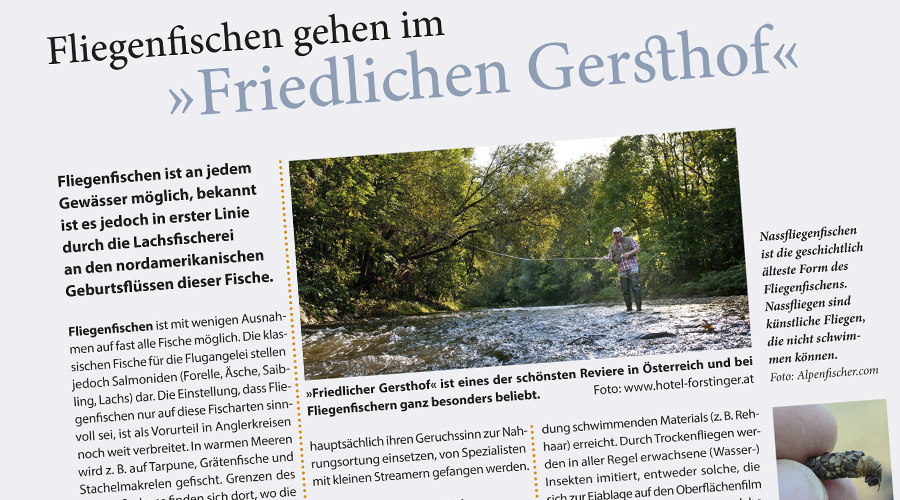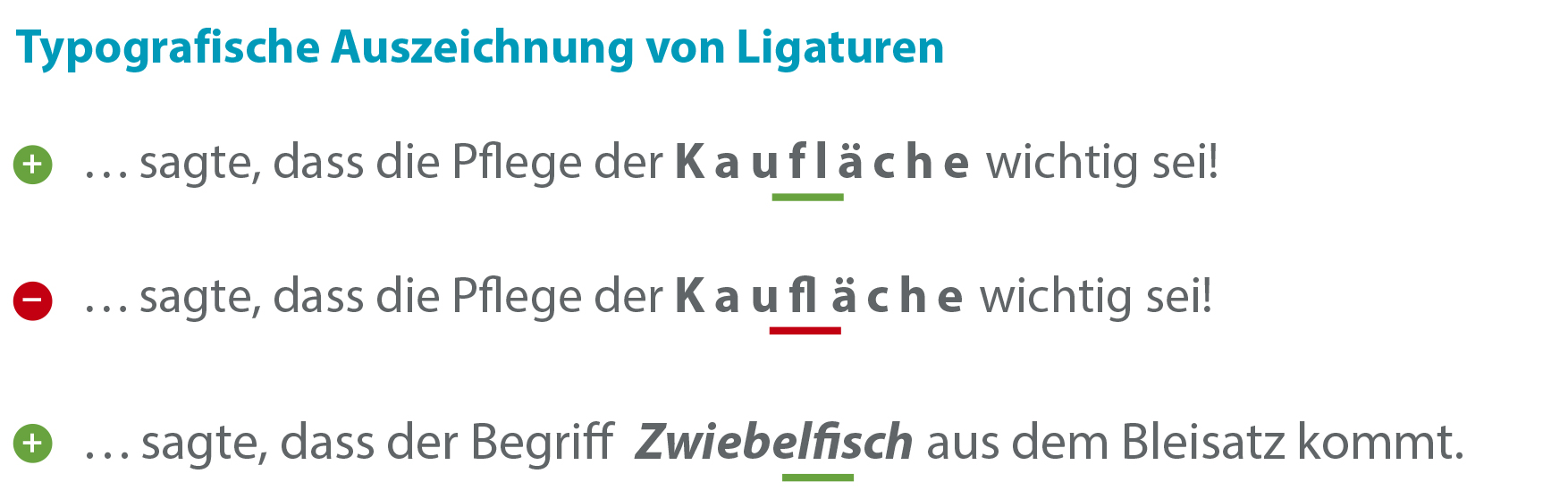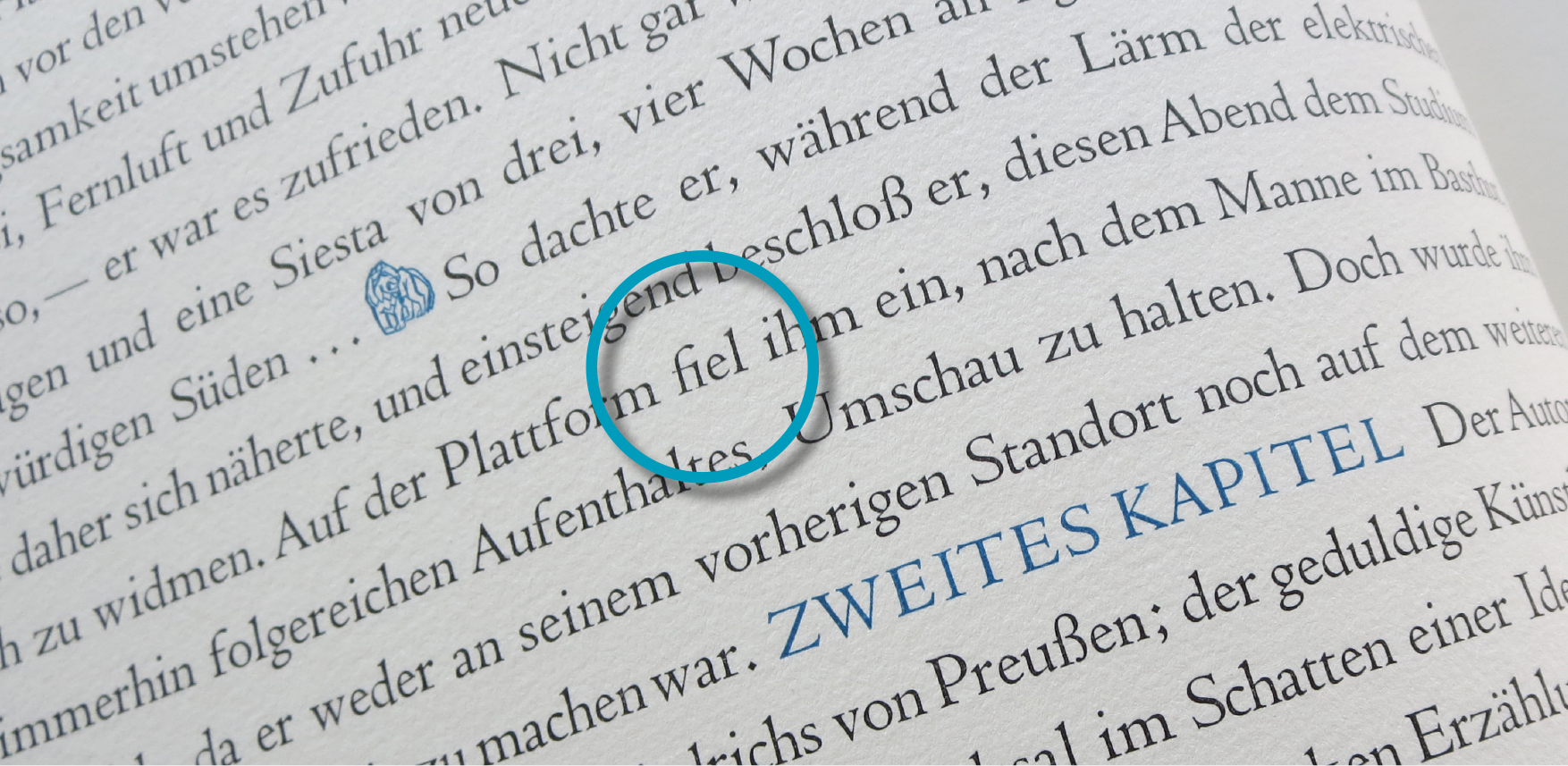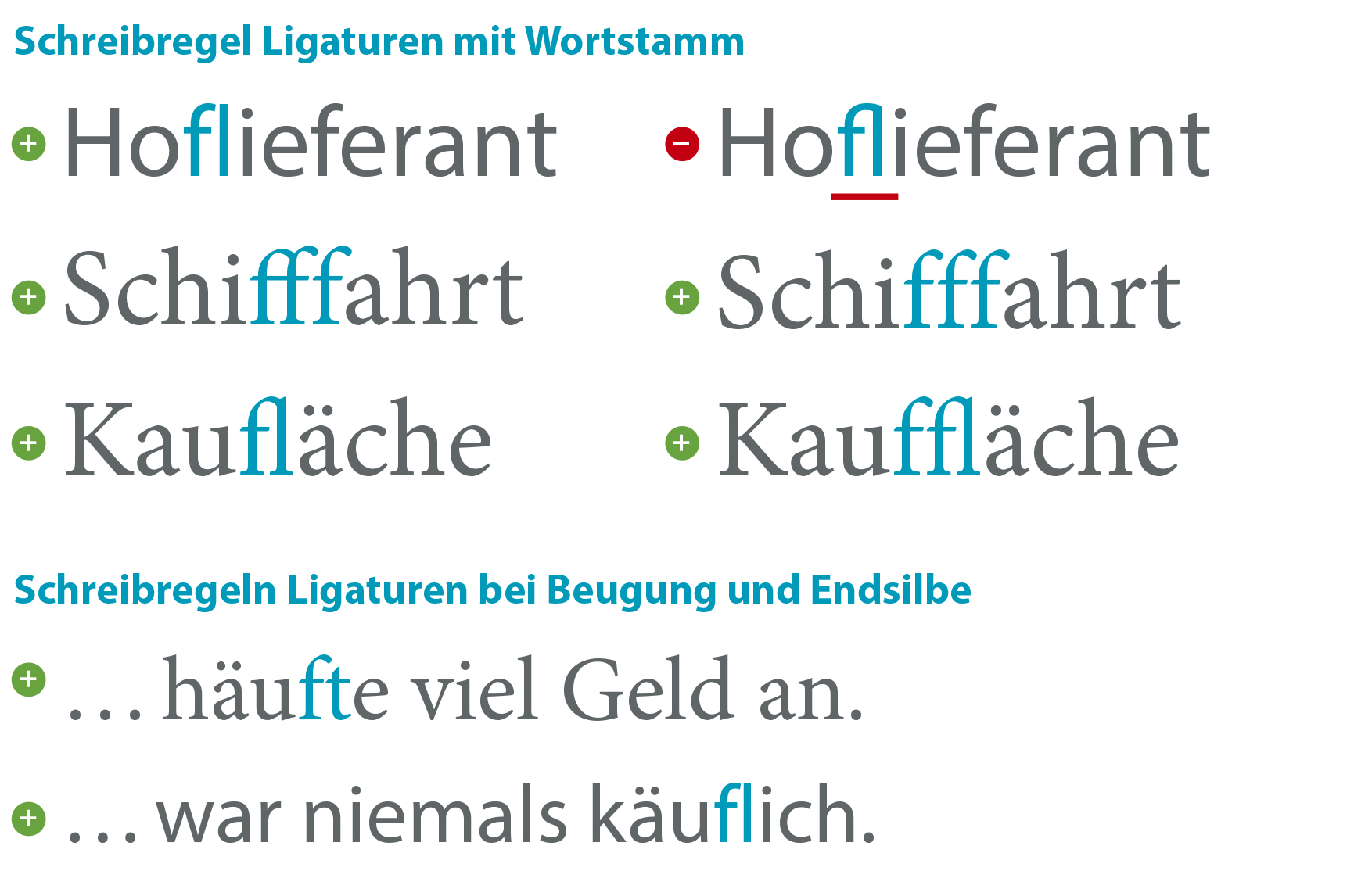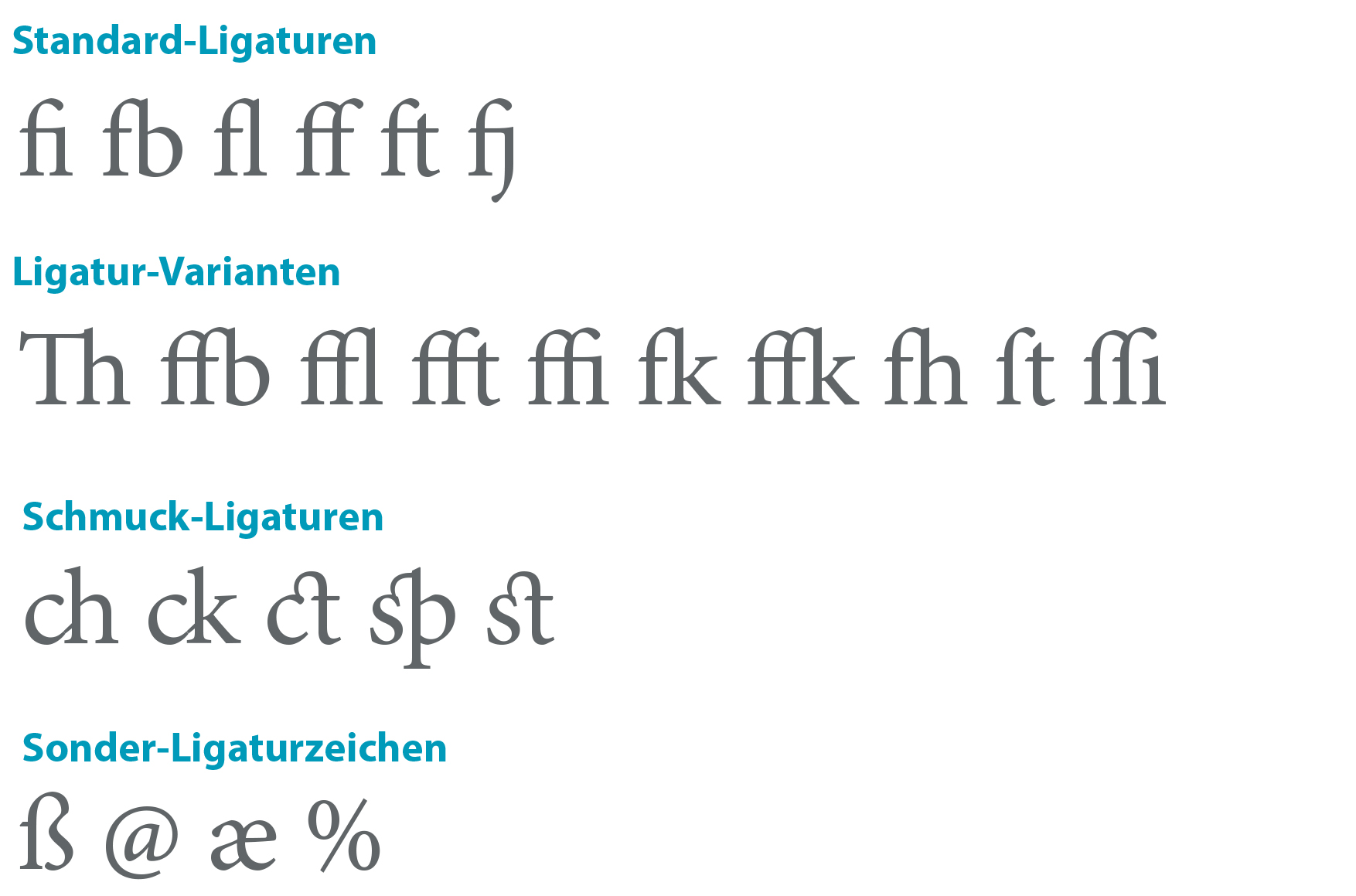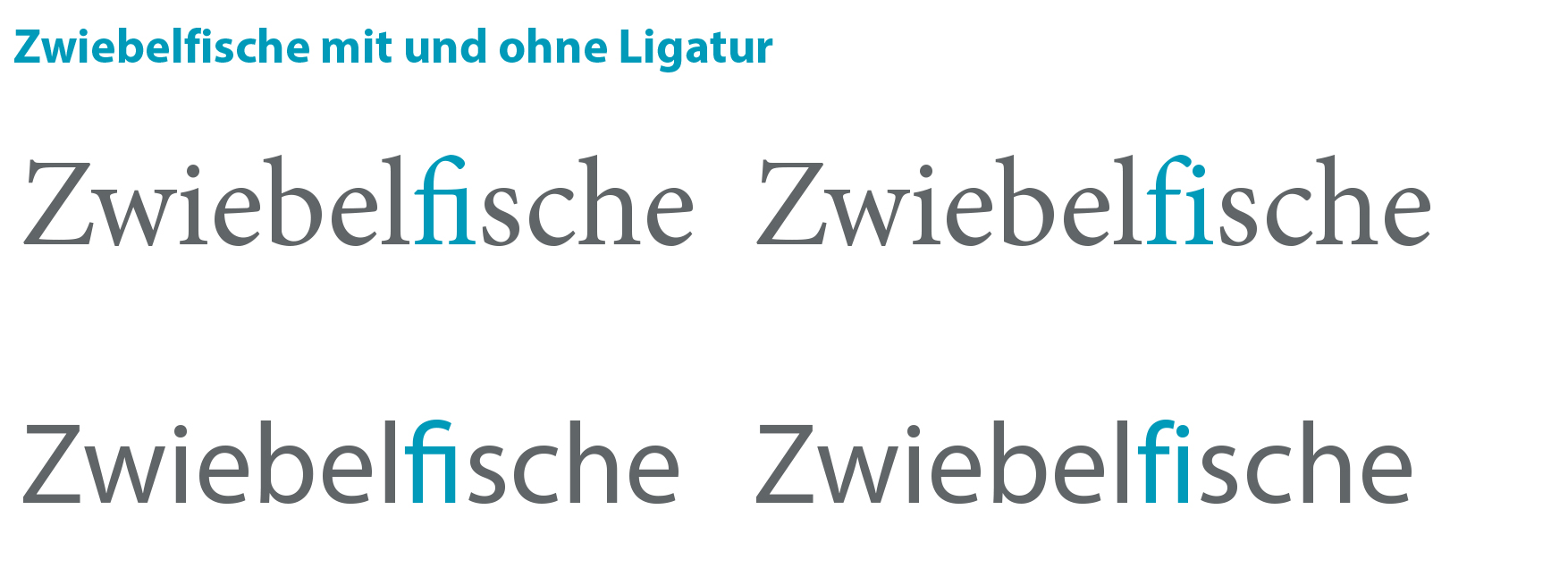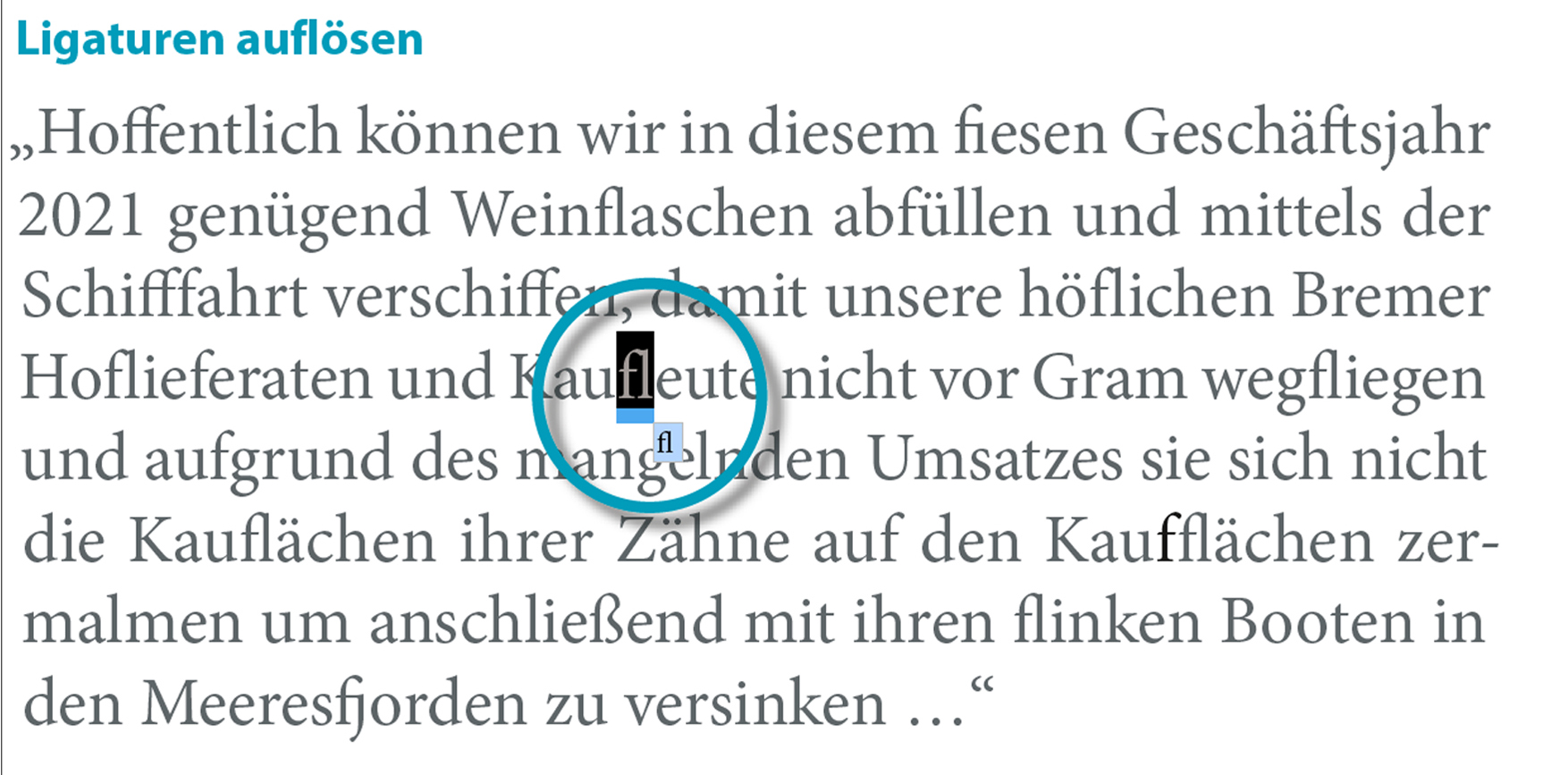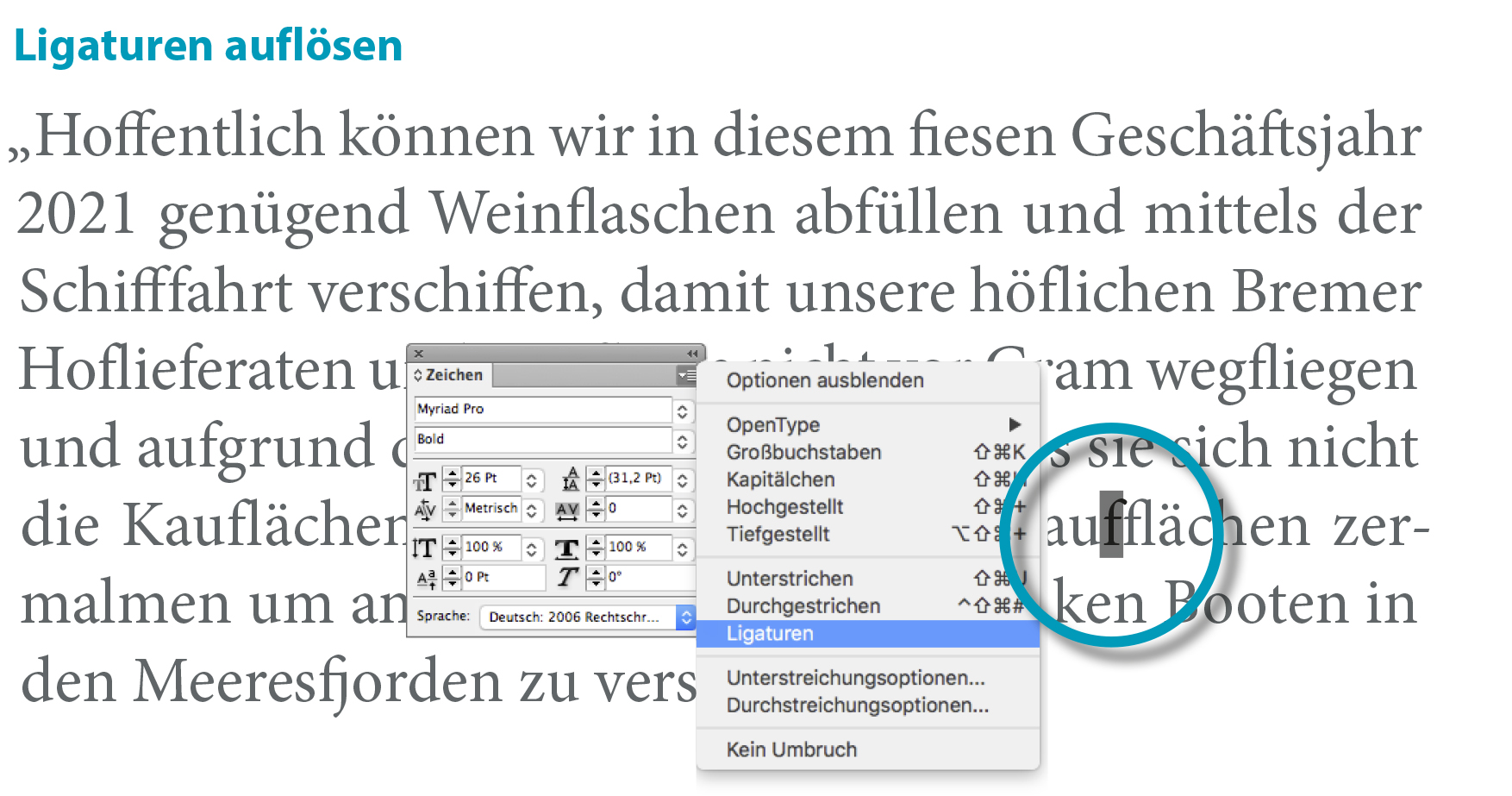
Typografie: Ligaturen im Schriftsatz – welche Regeln gelten bei der Anwendung und warum Ligaturen eigentlich nicht notwendig sind.
In meinem Online-Seminar zu Detail- und Lesetypografie werde ich oft gefragt, was genau Ligaturen sind, ob es Regeln bei der Anwendung im Schriftsatz zu beachten gibt und ob man Ligaturen überhaupt setzen sollte.
In diesem Beitrag möchte ich darauf eingehen, was genau Ligaturen sind, wie sie typografisch korrekt angewendet werden und auch, warum wir Ligaturen eigentlich gar nicht (mehr) brauchen.
Ligaturen, lat. ligatura = Verbindung, sind Verbindungen von zwei oder drei Buchstaben, die aufgrund zu großer Abstände durch Unterschneiden zu einem eigenen Zeichen werden; zum Beispiel f und i.
Durch diese optische Korrektur vermeiden Ligaturen unschöne Lücken in den Wörtern und verbessern den Lesefluss von Text. Ligaturen können in fast allen serifenlosen und Serifenschriften gesetzt werden, wobei aber nicht jeder Font automatisch über Glyphen mit Ligaturverbindungen verfügt.
Ligaturen finden ihren Ursprung im Bleisatz
Ligaturen kommen aus dem Bleisatz und hatten als Lettern im Satzkasten nach DIN 16502 ein eigenes Fach. Einzelne Lettern konnten technisch keinesfalls unterschnitten werden. Das untere Bild zeigt den Ausschnitt aus einer bibliophilen Buchausgabe, die im Handsatz unter Verwendung der Ligatur fi als einzelne Letter gesetzt wurde. Ohne diese Unterschneidung würden die Buchstaben f und i eine zu große Lücke bilden und ein unschönes Satzbild abgeben.
Beachten Sie bei der Ligatur den fehlenden i-Punkt der Glyphe. Es wurde eine Satzschrift aus der Schriftgruppe der Venezianischen Renaissance-Antiqua gewählt. Diese zeichnet sich unter anderem durch die deutliche Tropfenform des f-Schweifes aus und lässt den i-Punkt überflüssig werden.
Diese Ligaturarten gibt es
Für meine praktische Arbeit teile ich den Umgang mit Ligaturen ein in Standard-Ligaturen, also solche, die am häufigsten vorkommen sowie Schmuck-Ligaturen und Sonder-Ligaturzeichen ein. Ligatur-Varianten sind bei vielen Fonts eher seltener vorhanden.
Standard-Ligaturen vermeiden mögliche Leerräume zwischen Glyphen und verbessern den Lesefluss im Text, Schmuck-Ligaturen sind bestens geeignet, den Satz ästhetischer oder anspruchsvoller zu gestalten und Sonder-Ligaturzeichen sind solche, die aus Gründen von Zeitersparnis durch schnelleres Schreiben gebildet werden. Beachten Sie beim Titelbild oben die schöne Schmuck-Ligatur, die aus s und t gebildet wurde.
Wenn Ligaturen nicht erwünscht sind
Kennen Sie Fälle, in denen der Auftraggeber durch Ligaturbildung im Schriftsatz den fehlenden i-Punkt eines Wortes bemängelt oder das Lektorat/Korrektorat aufgrund einer Schreibregel eine fehlerhafte Ligaturbildung markiert hat? Wenn Sie aus solchen Gründen Ligaturen im Schriftsatz grundsätzlich vermeiden möchten, dann können Sie in Adobe InDesign als Voreinstellung im Menü Schrift / Zeichen / Untermenü Ligaturen durch Weglassen Häkchen die automatische Schreibung von Standard-Ligaturen deaktivieren. Achten Sie darauf, dass dabei entgegen der Abbildung unten kein InDesign-Dokument geöffnet sein darf, da sich diese Einstellung dann nur auf das geöffnete Dokument bezieht und nicht als grundsätzliche Voreinstellung aktiviert wird.
Im regulären Absatztext sind Ligaturen nicht unbedingt nötig
Echte Ligaturen kommen aus dem Bleisatz, weil einzelne Bleilettern nicht unterschnitten werden konnten. Im heutigen Digitalsatz jedoch sind aufgrund des guten Kernings von Schriften zu große und kleine Abstände zwischen kritischen Zeichen optisch lückenlos ausgleichbar. Dadurch entfällt die Funktion einer Ligatur, so dass man im Schriftsatz auf sie ganz verzichten kann. Im barrierefreien Satz nach DIN 1450 zur besseren Leserlichkeit von Text sollen Ligaturen ohnehin nicht verwendet werden.
Der Satz von Ligaturen kennt Schreibregeln
Außer Schmuck- und Sonder-Ligaturen dürfen im Schriftsatz die Standard-Ligaturen nicht immer angewendet werden – auch wenn sie noch so schön aussehen.
Wichtigste Grundregel:
Ligaturen werden nicht verwendet, wenn sie als Wortverbindung zwischen zwei Stammwörtern gesetzt werden, Beispiel Kaufleute fl ohne Ligaturverbindung – also zwei Wortstämme kaufen und Leute.
Weitere Regeln:
Ligaturen werden ebenfalls nicht gesetzt bei Beugungen am Ende eines Wortes, Beispiel häufte und bei Endsilben, Beispiel käuflich.
Ligaturen im Schriftsatz auflösen oder eine Ligatur setzen
Das automatisch richtige Setzen von Ligaturen funktioniert in Adobe InDesign auch bei Auswahl der aktuellen Rechtschreibprüfung nur unzureichend. Daher sollten Texte mit aktivierter Ligaturschreibung unbedingt Korrektur gelesen werden – am besten durch ein Lektorat. Neben den wichtigsten hier gezeigten Beispielen gibt es noch einige weitere Schreibregeln, in denen Ligaturen nicht gesetzt werden.
Wenn Sie in einem Text eine einzelne Ligatur auflösen oder aus zwei Glyphen eine Ligatur erstellen möchten, ohne den Ligatursatz generell zu deaktivieren, so können Sie mit dem Cursor die gesetzte Ligatur oder die beiden Buchstaben, aus denen Sie eine Ligatur erstellen wollen, aktivieren und dann unmitteldar im Schriftsatz das jeweilige Zeichen auswählen.
Teste dich selbst
Wann dürfen hier Ligaturen verwendet werden?
„Hoffentlich können wir in diesem fiesen Geschäftsjahr 2021 genügend Weinflaschen
abfüllen und mittels der Schifffahrt verschiffen, damit unsere höflichen Bremer Hoflieferaten und Kaufleute nicht vor Gram wegfliegen und aufgrund des mangelnden Umsatzes sie sich nicht die Kauflächen ihrer Zähne auf den Kaufflächen zermalmen um anschließend mit ihren flinken Booten in den Meeresfjorden zu versinken …“